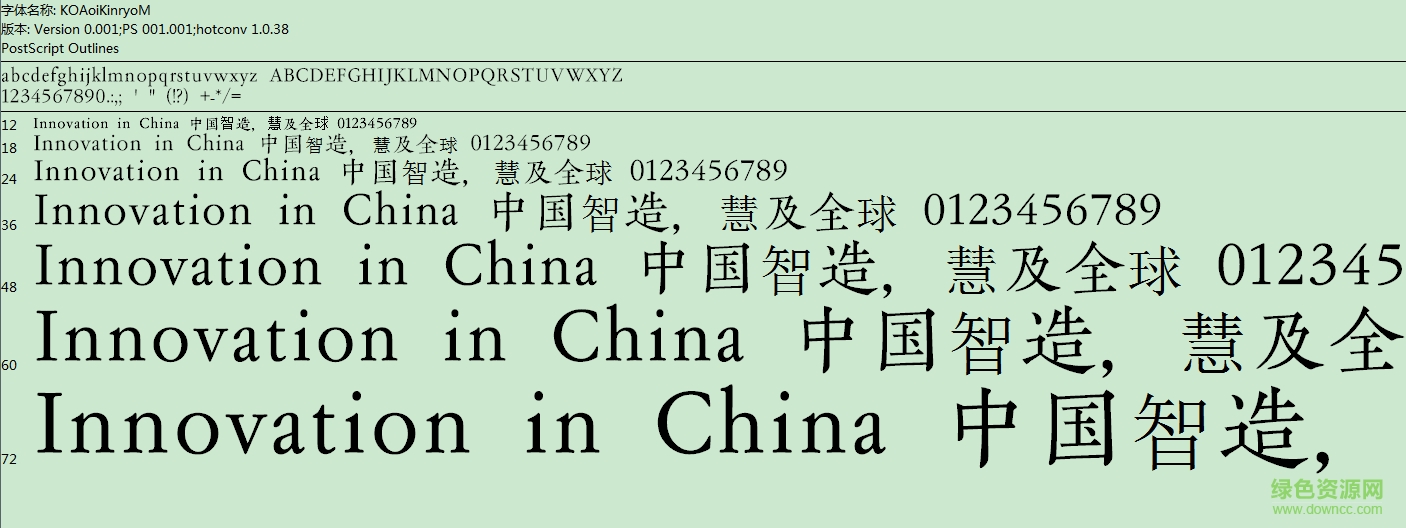
欣喜堂金陵明朝體是一款非常漂亮的字體,這款字體端正,字體線條粗細(xì)均勻,字形簡(jiǎn)潔大方,并且適用的范圍非常的廣泛,有需要的朋友歡迎來綠色資源網(wǎng)下載使用!
欣喜堂金陵明朝體簡(jiǎn)稱為欣喜堂金陵體,該字體是在金陵明朝體1300字版的基礎(chǔ)上分析其筆畫結(jié)構(gòu)特征,設(shè)計(jì)的簡(jiǎn)體版,目前將近2700字,字體線條粗細(xì)均勻,字形端正大方得體,整體效果非常統(tǒng)一,且字庫(kù)完整,可以廣泛應(yīng)用于廣告、通知欄、電影、電視劇片頭以及內(nèi)容用字等領(lǐng)域,有需要的朋友可以免費(fèi)下載收藏。